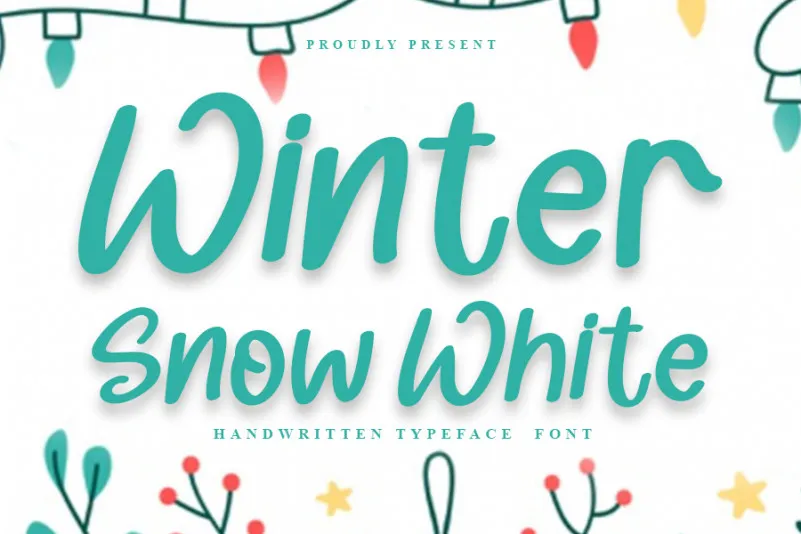
Winter Snow White Display Font – Download Grátis
Winter Snow White Display Font é uma elegante fonte feita à mão que transmite sutileza e alegria através de sua forma curvilínea e delicada. Suave como neve, esta fonte será perfeita para personalizar um convite de casamento ou cartões, criando um toque romântico e único em qualquer design. Perfeito para aqueles que buscam uma escrita alegre e delicada para suas criações gráficas, essa fonte traz uma sensação fresca ao seu trabalho, tornando-o ainda mais especial. Ideal tanto para cartões de aniversário quanto para convites nupciais, Winter Snow White Display Font é perfeito para aqueles que querem dar um toque singular e encantador a seus projetos visuais.